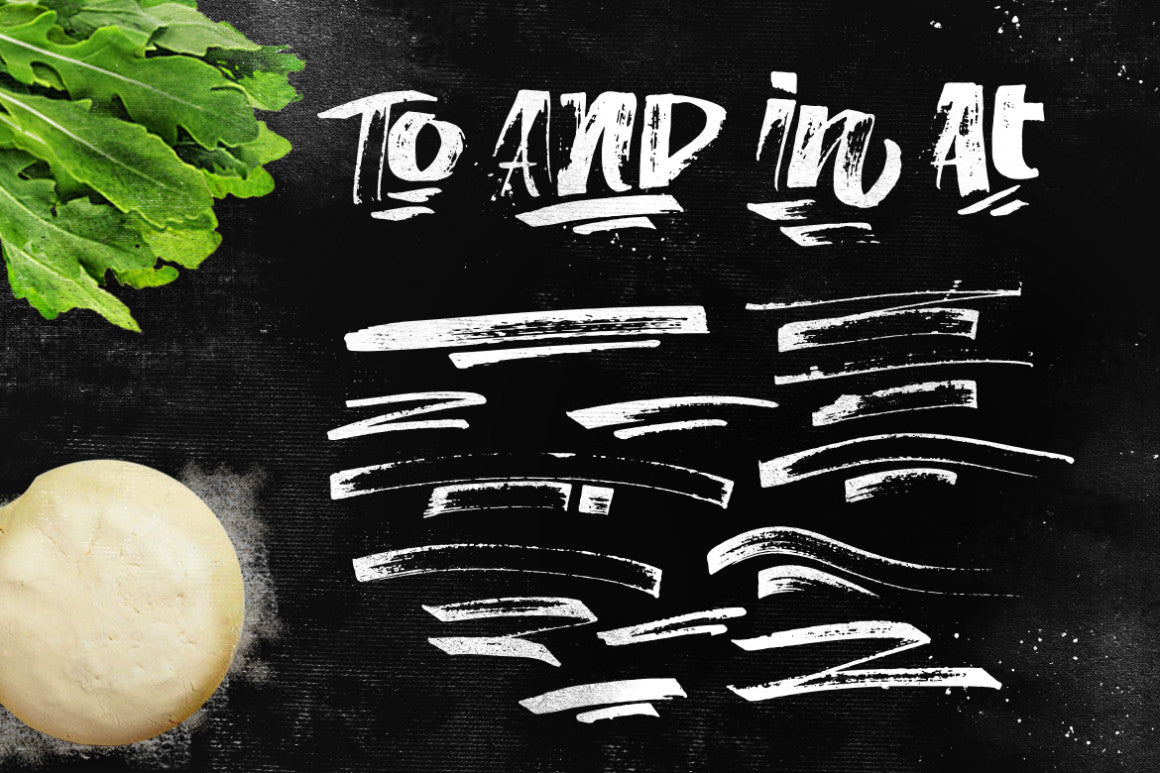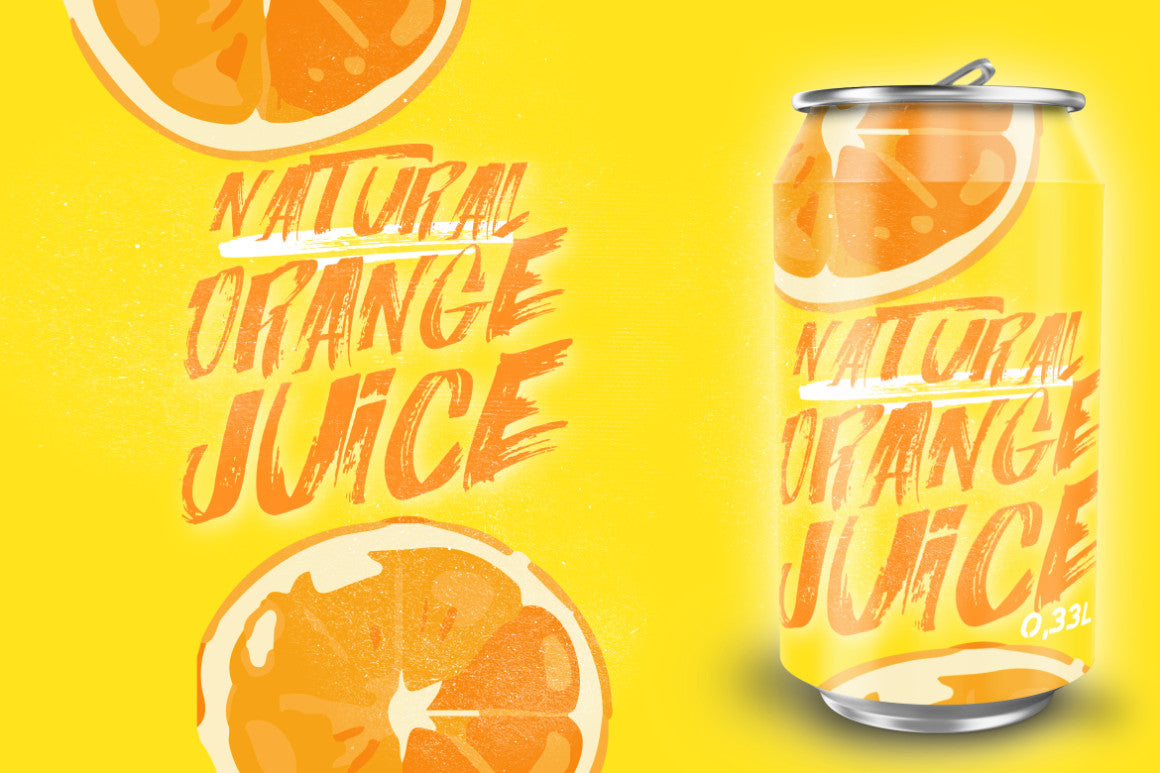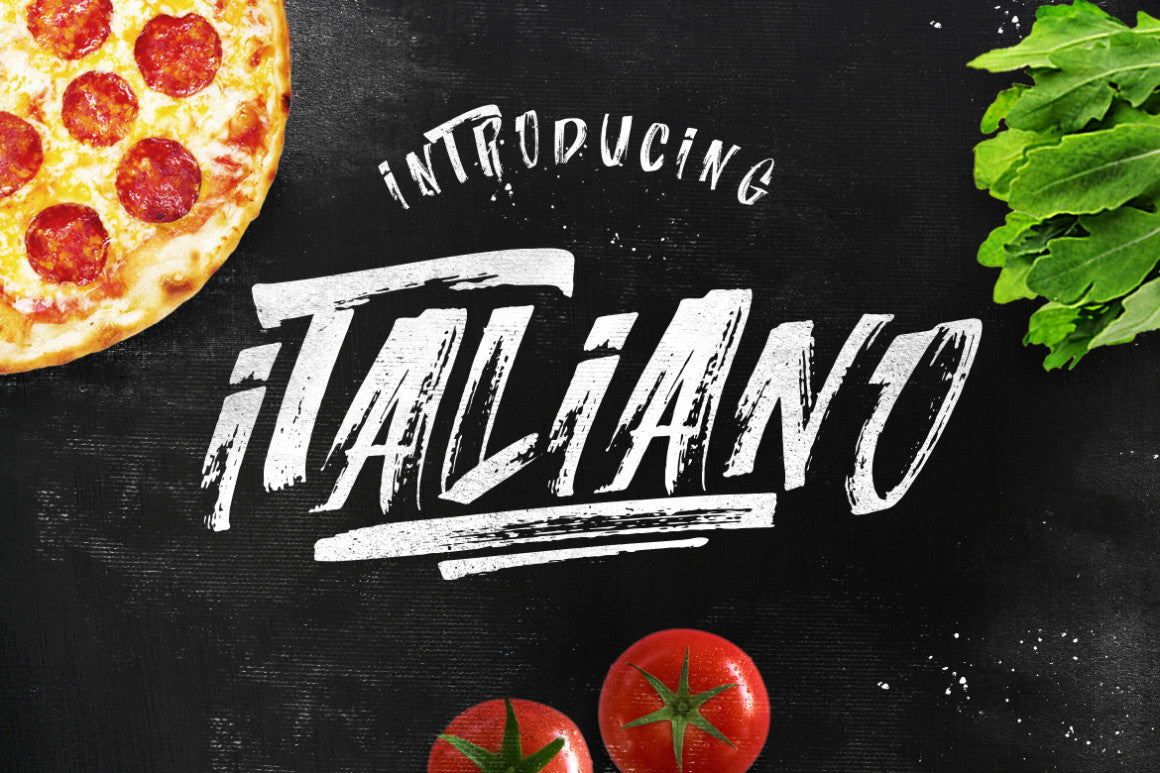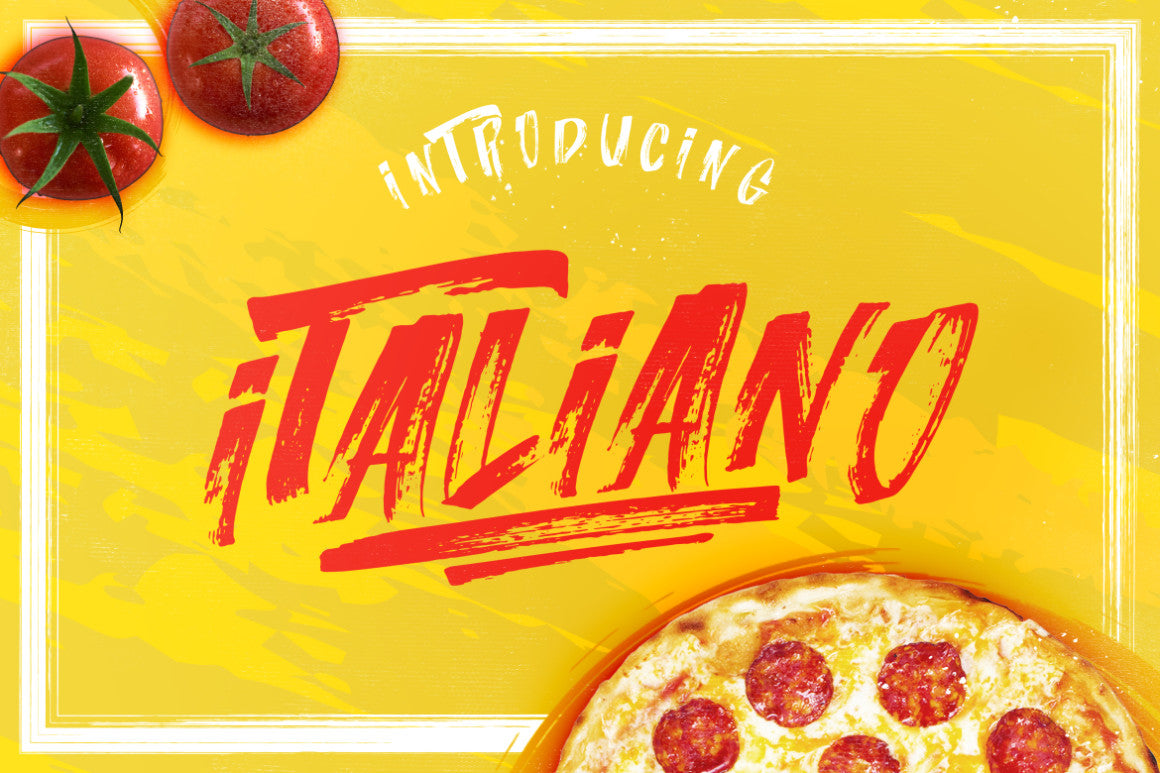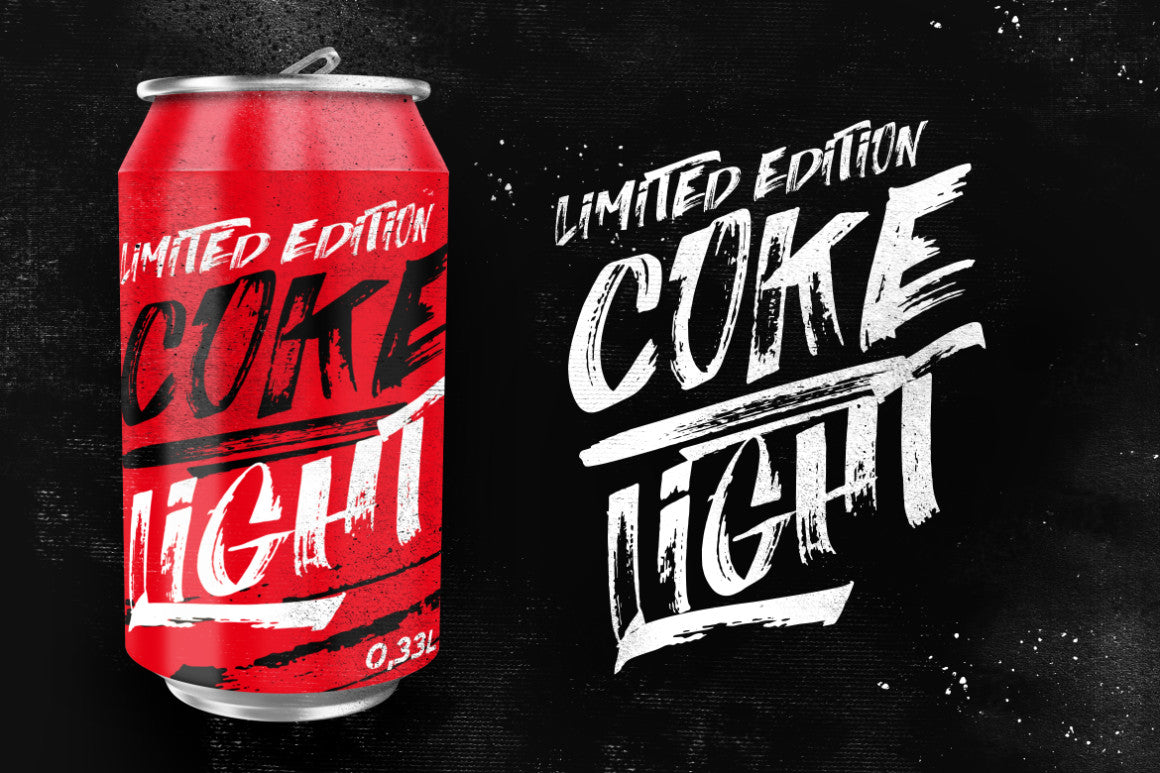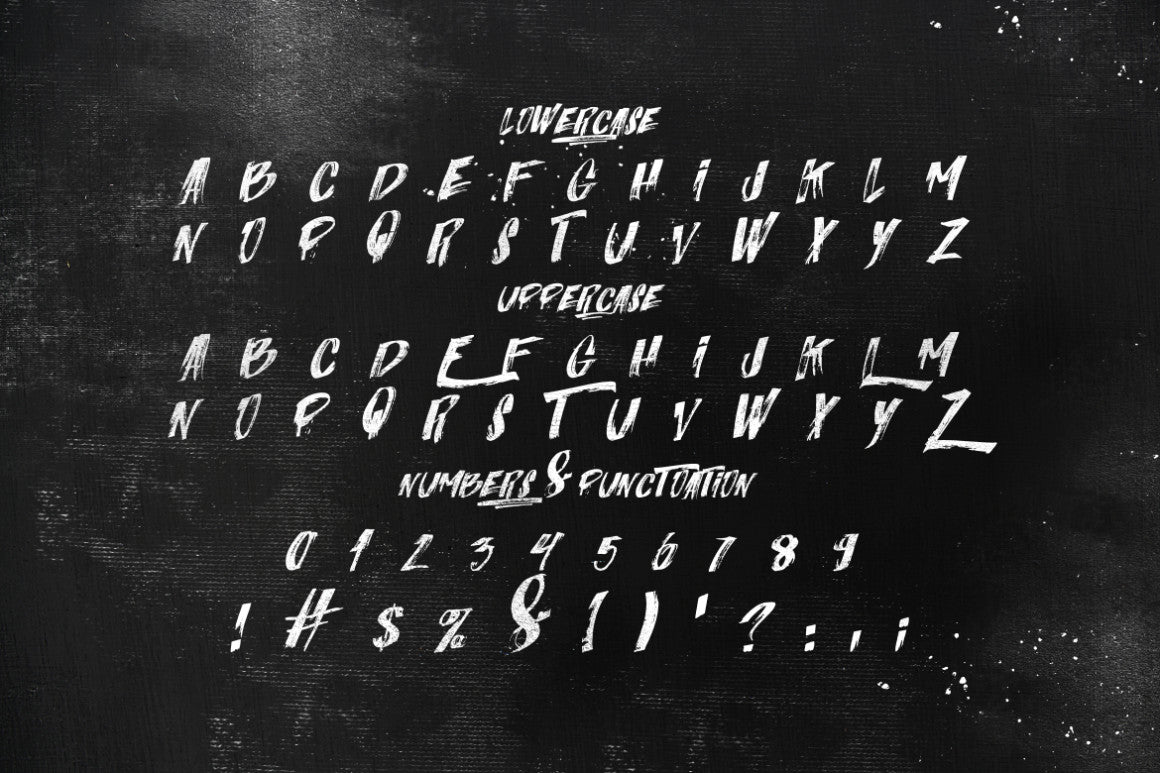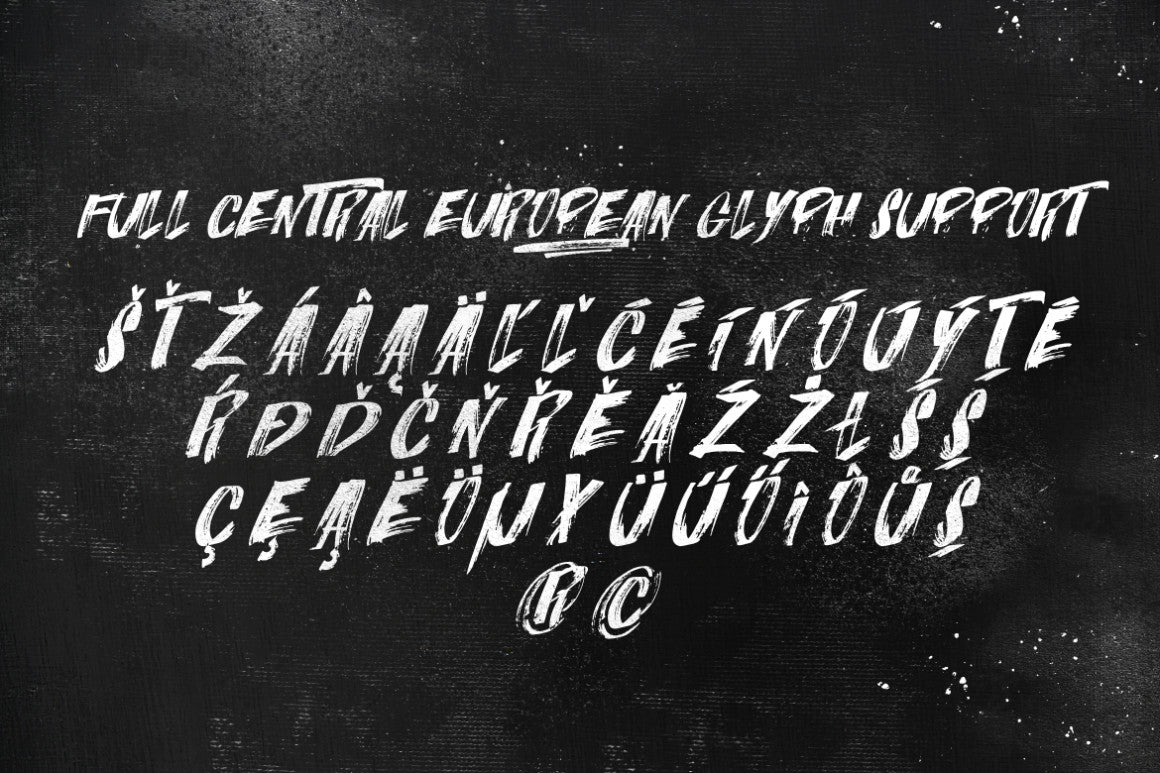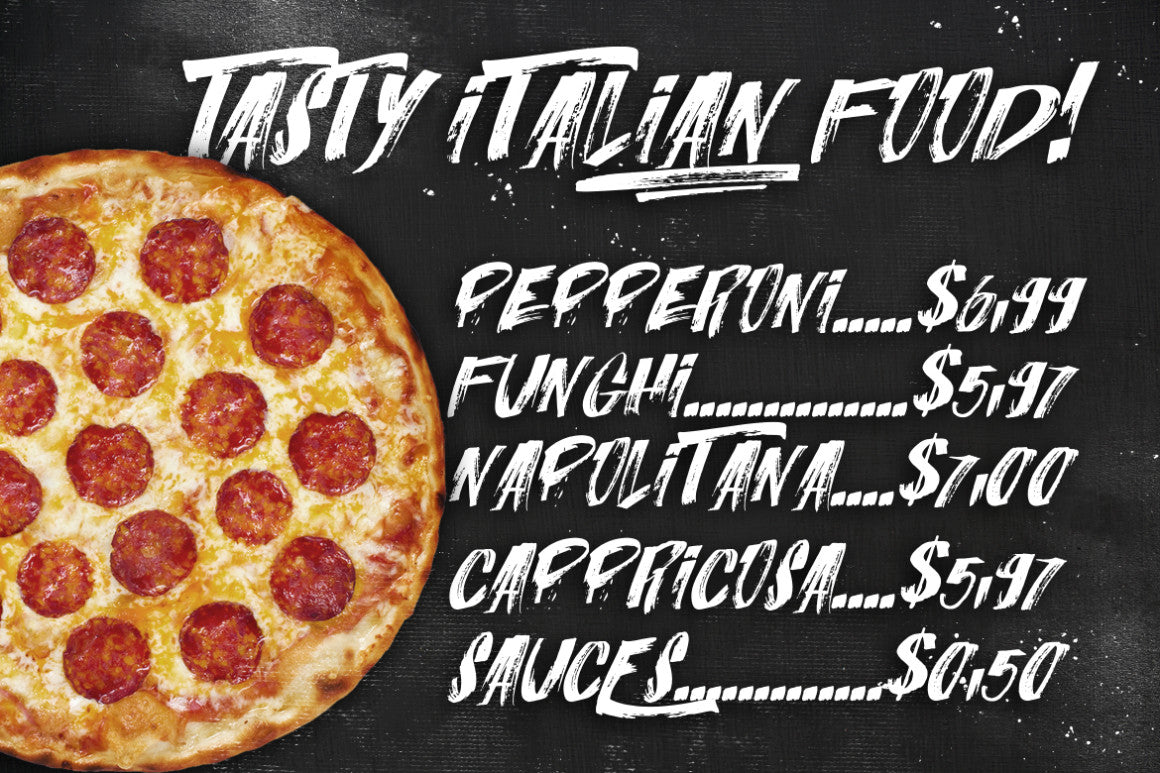
ITALIANO ブラシフォント +Extras
Italianoは、中央ヨーロッパのグリフを網羅したブラシフォントで、通常版と斜体版があります。エネルギーに満ちたフォントで、素早いストロークとシャープなエッジが特徴です。力強いメッセージに最適です。ロゴ、名札、手書きの引用文、製品パッケージ、商品、ソーシャルメディア、グリーティングカードなど、様々な用途にお使いいただけます。また、Tシャツのデザインやその他の衣料品にも最適です。
ITALIANO - AZの完全なセットを含む、すべての大文字を含む手書き風フォント。中央ヨーロッパの文字もすべてサポートしています。大文字と小文字を組み合わせて、個性的なテキストスタイルを作成できます。
ITALIANO SLANT - AZ の完全なセットを持つすべての大文字を含む 18° 傾斜の手書きフォントで、中央ヨーロッパの文字全体をサポートします。
イタリア語スワッシュ - EXTRA 13 下線付きのスワッシュと6つのスプラッターをペイントします。AからZまでの任意の文字を入力し、通常の文字と組み合わせて使用できます。